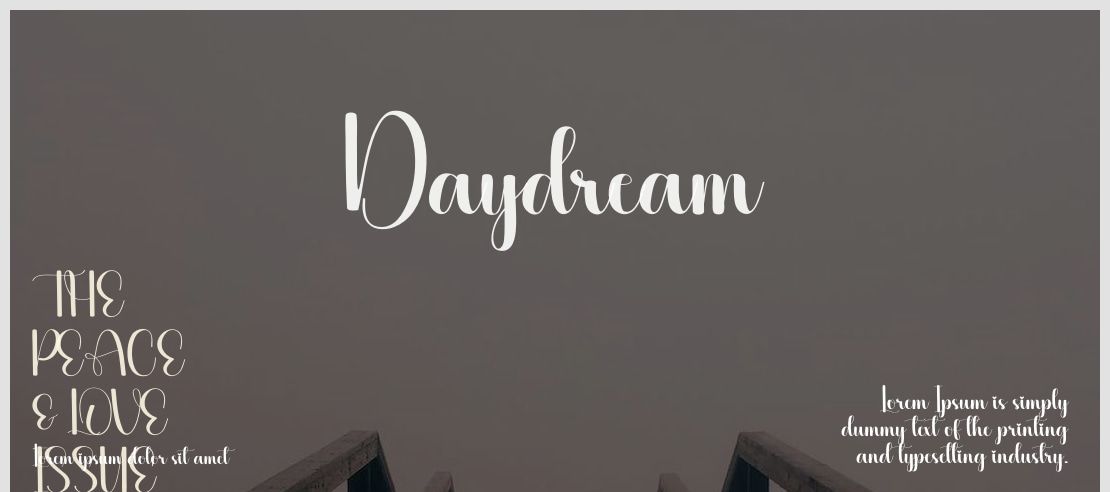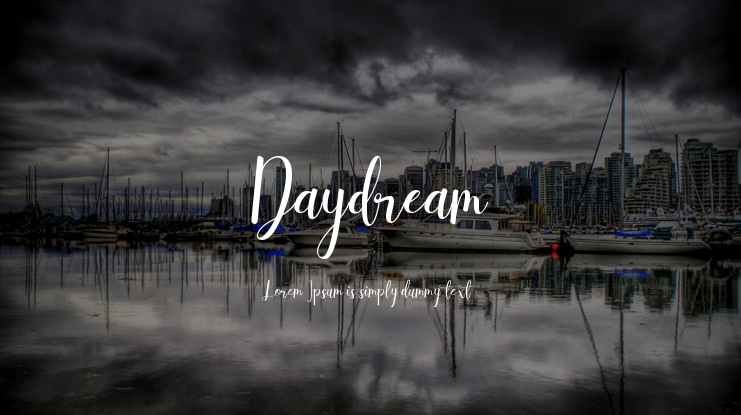
Font Daydream là gì?
Daydream là phông chữ thuộc dòng Script mang phong cách vô cùng mềm mại, lãng mạn và đầy mơ mộng. Đặc trưng của Daydream là đường nét uốn lượn nhịp nhàng, tạo cảm giác thư thái và bay bổng như những đám mây.
Đây là phông chữ hoàn hảo cho các thiết kế thiệp chúc mừng, bao bì các sản phẩm chăm sóc sắc đẹp, nến thơm thủ công hoặc hộp quà tặng kỷ niệm ngày cưới.
Vẻ đẹp của Daydream nằm ở sự tự nhiên trong từng nét nối. Bản download font Việt hóa Daydream đã được căn chỉnh kerning hoàn hảo, giúp các dấu tiếng Việt không bị chồng chéo lên nhau, giữ trọn vẹn tinh thần thơ mộng của bộ chữ.
Lưu ý: Font Daydream có cấu trúc chữ mảnh và bay bổng. Khi in trên chất liệu vải túi canvas, bạn cần kiểm tra lưới in để mực không bị loang làm mất nét chữ.
Font chữ Daydream Việt hóa có ứng dụng như thế nào khi thiết kế và in ấn?
Vẻ thanh thoát của font chữ Daydream giúp ấn phẩm trở nên độc đáo và giàu cảm xúc:
- Thiết kế bao bì giấy: Chữ Daydream in trên nhãn dán decal tạo phong cách tối giản và thư giãn cho bao bì như hộp và túi giấy.
- Sản xuất hộp đựng: Những lời chúc viết bằng font chữ Daydream giúp sản phẩm tri ân trở nên ấm áp và mang đậm dấu ấn cá nhân của thương hiệu.
- In logo lên bộ ấm chén sứ: Hình ảnh chữ nghệ thuật in nung trên men sứ trắng là ấn phẩm cho việc đối ngoại vô cùng thanh nhã và trang trọng.
- Trang trí voucher và thẻ VIP: Tạo sự khác biệt cho khách mời thông qua tà chữ mềm mại sắc sảo trên chất liệu giấy mỹ thuật cao cấp.
Sử dụng font chữ Daydream cần lưu ý gì?
Để họa tiết chữ uốn lượn này hiển thị đẹp trên thành phẩm thực tế, designer cần chú trọng:
- Xử lý màu sắc pastel: Daydream cực kỳ hợp với các tông màu nhẹ nhàng như hồng phấn, xanh mint. Bạn nên thiết lập hệ CMYK chuẩn để màu in không bị bợt.
- Phối hợp phông chữ: Nên dùng Daydream cho các tiêu đề ngắn và kết hợp cùng phông Sans-serif đơn giản cho các đoạn nội dung chi tiết để bố cục thoáng đạt.